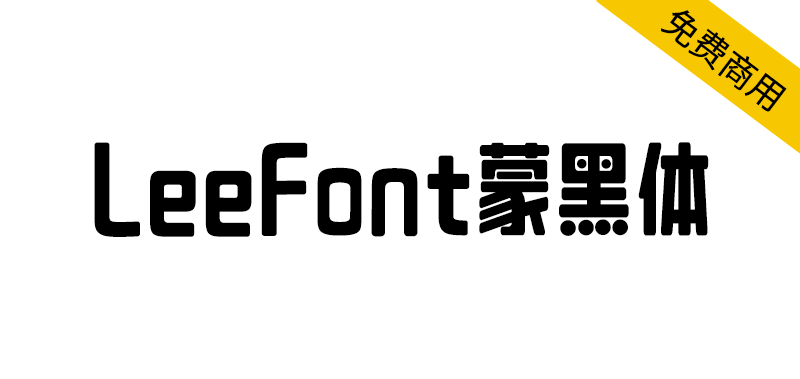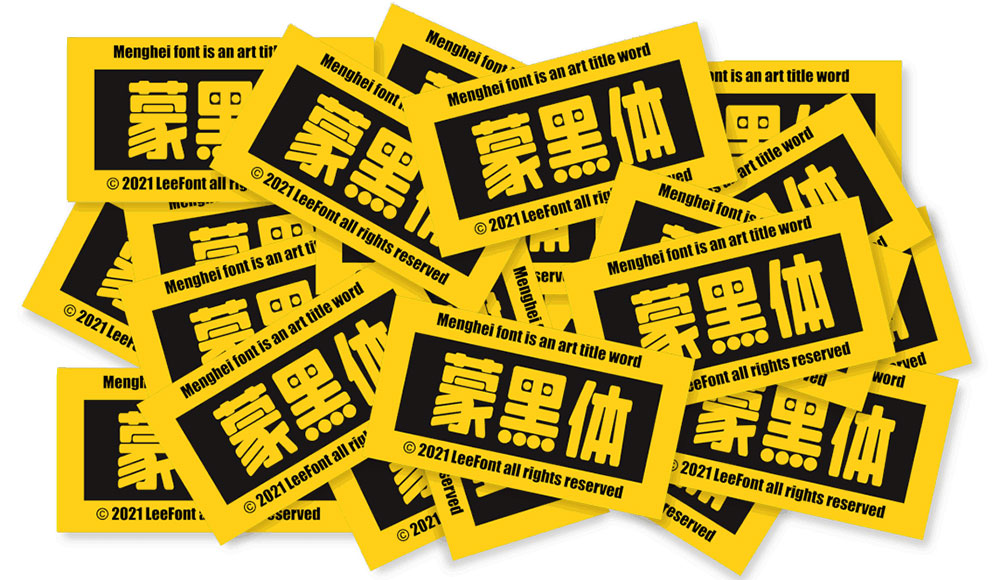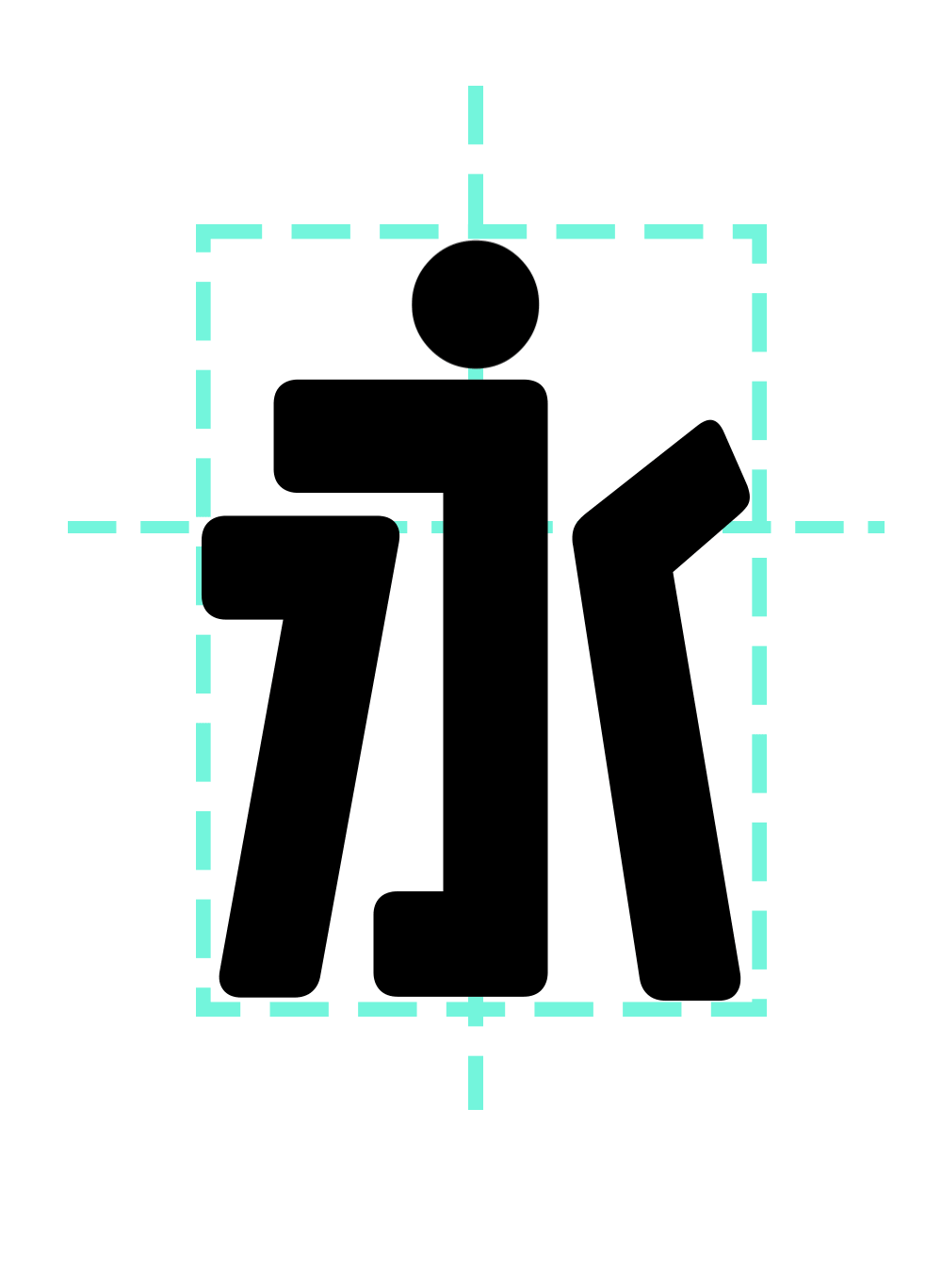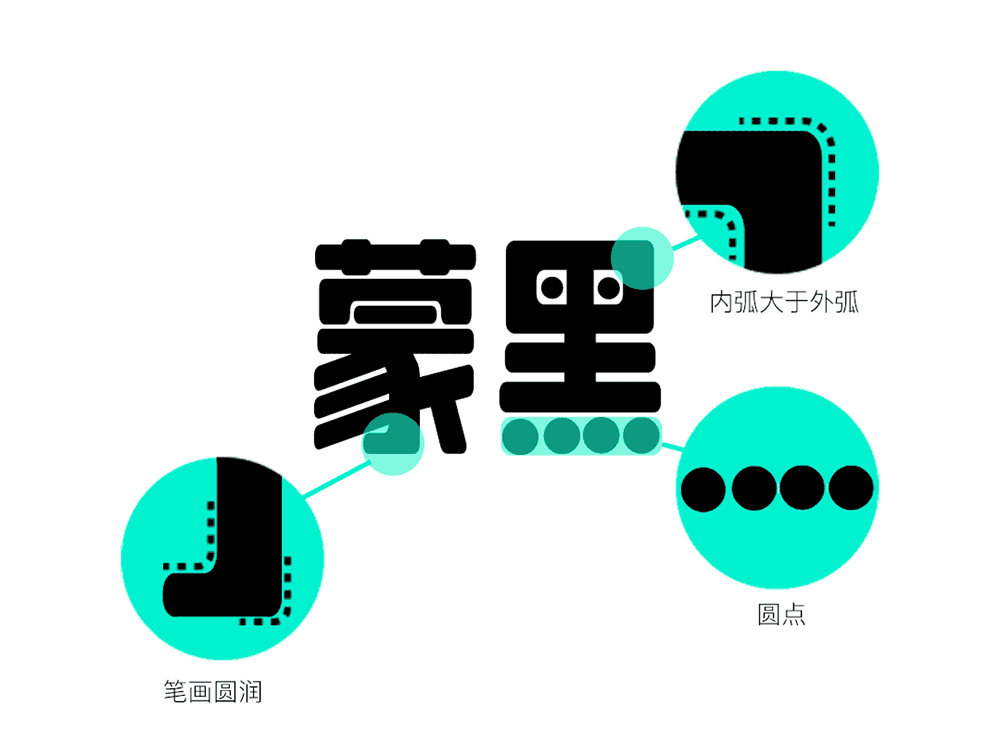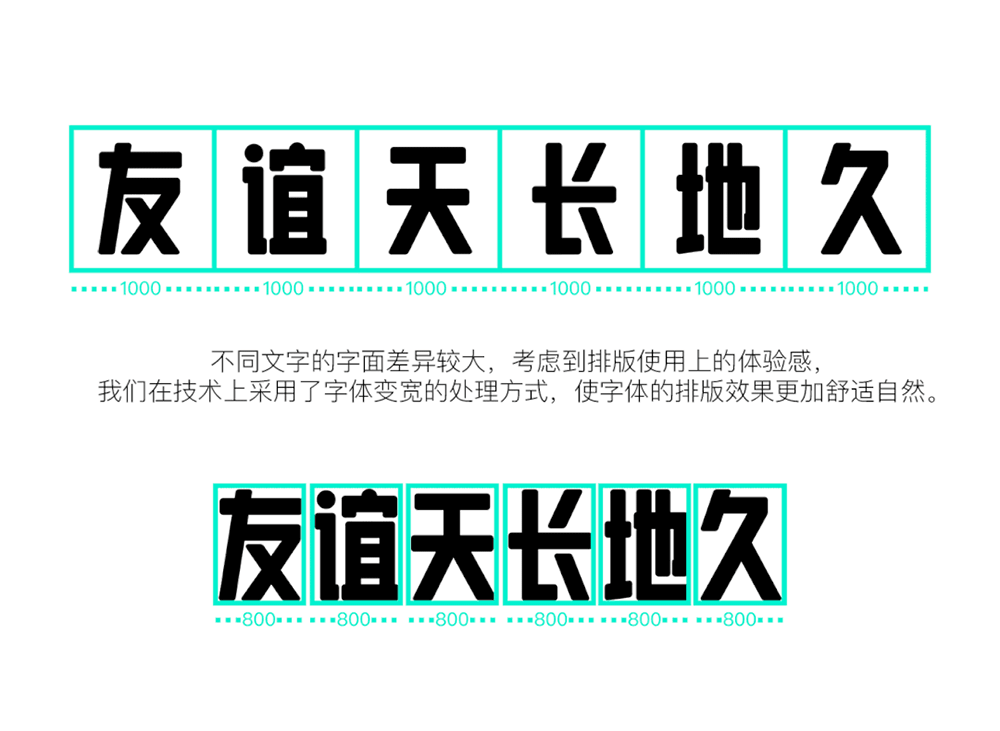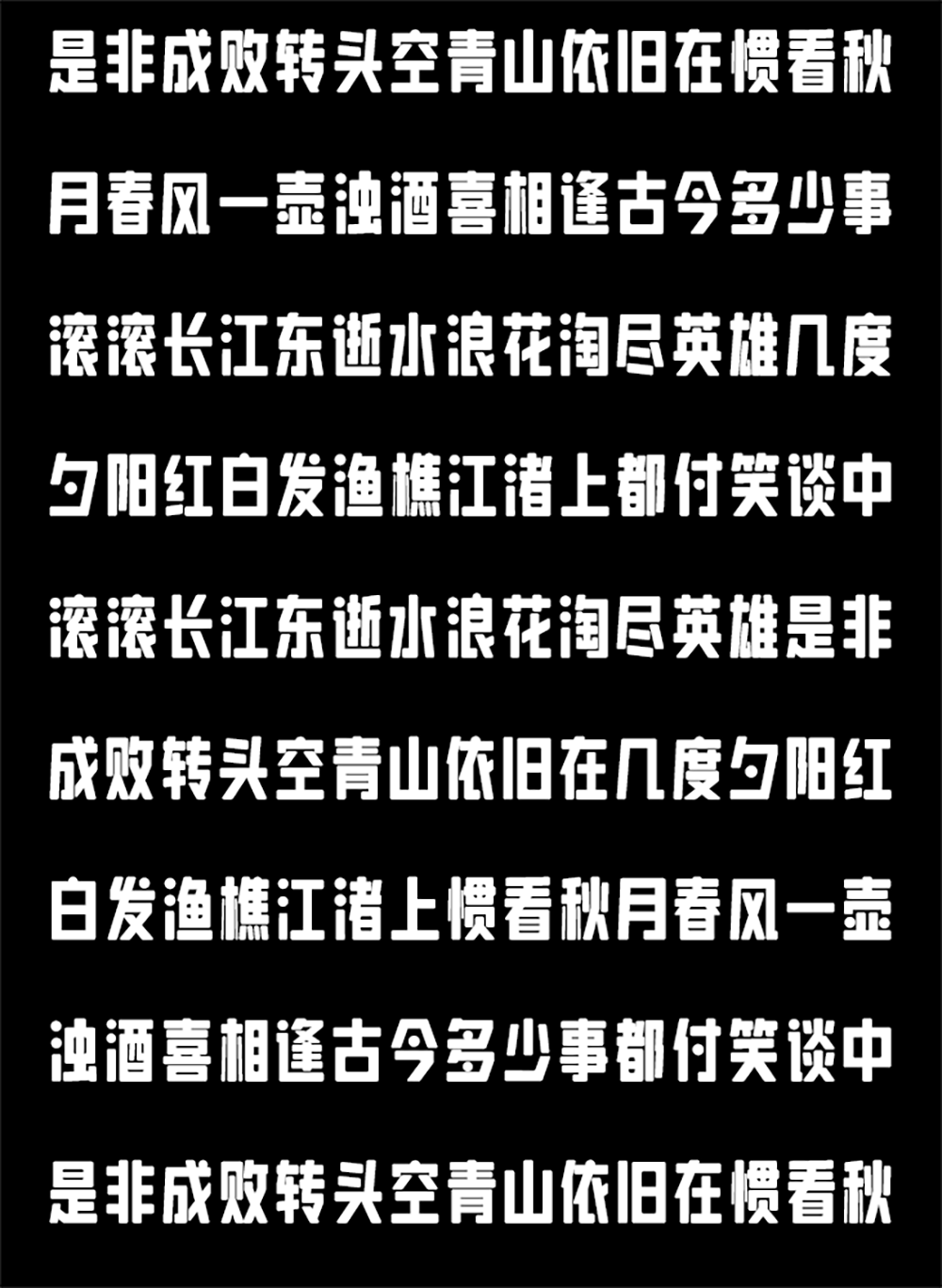
【LeeFont蒙黑体】美术标题字,字形偏长,结构饱满,活泼
LeeFont蒙黑体(乐字蒙黑体)是“乐字”制作的一款艺术美术标题字体,它的整体字形偏长,字面结构饱满,有稳重中具备力量感的同时笔画结构蕴含乐趣在其中,使其多了一些生动活泼,属于人文、灵动、现代、活泼、几何、欢乐风格,适用于标志、广告、书籍、包装、影视、广告等场景。
【LeeFont蒙黑体】美术标题字,字形偏长,结构饱满,活泼